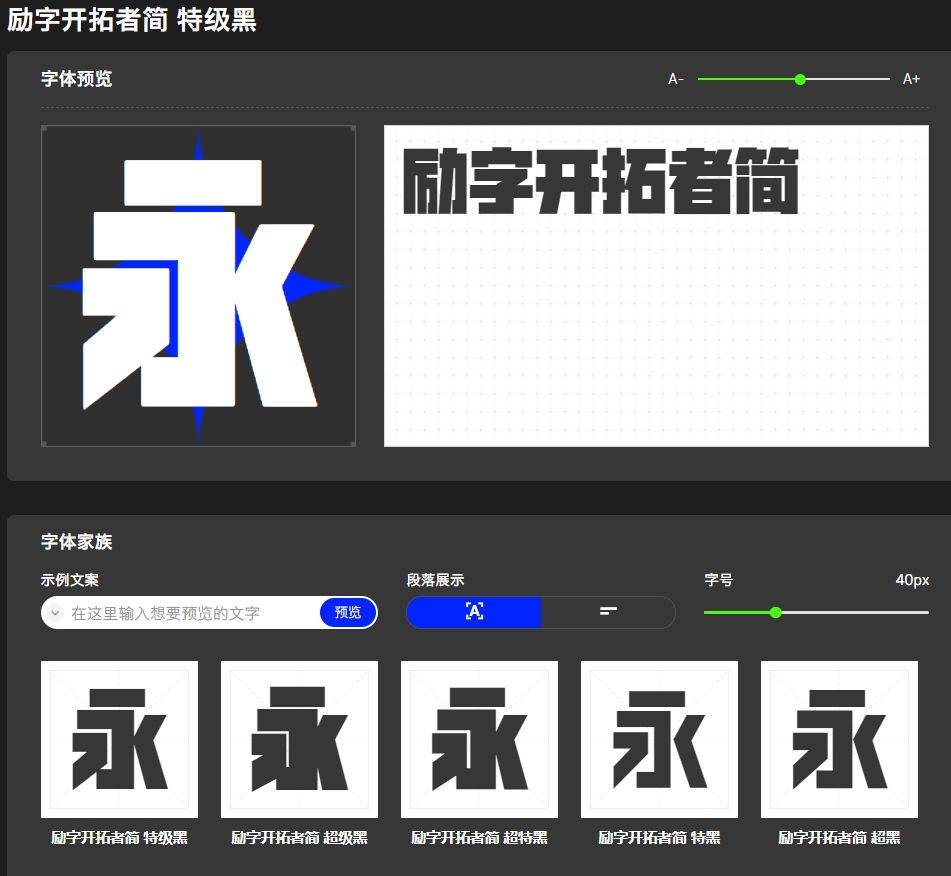
励字开拓者简,一款大气的海报字体!
在海报设计中,文字是传递信息的重要元素,而选择一款合适的字体则能大大提升海报的视觉效果。本文将推荐一款大气、醒目的海报字体——励字开拓者简,帮助您在设计中脱颖而出。
励字开拓者简,字型方正,中宫较大,重心适中。全部采用直线笔画,笔画横平竖直,棱角分明,笔画特点简约,起笔和收笔以平切为主,内部几何处理空间均匀,整体平衡。部分钩笔画进行去钩处理,撇、捺、点运用竖直的处理方法,带有强烈的镜像视觉效果。励字开拓者系列化共5款家族字体,实现由正文到标题的平滑过度,适用各场景的应用。此款字体为包含常用的又、双、叒、叕、囍、雷、靁、䨻、火、炎、焱、燚、水、沝、淼、㵘、牪、龖等网红流行用字。
在选择大气海报字体时,我们要考虑海报的设计风格、主题以及所要传达的信息。一款合适的字体能够让文字与设计相互辉映,增强海报的整体效果。希望本文的推荐能够帮助您在海报设计中取得更好的成果。